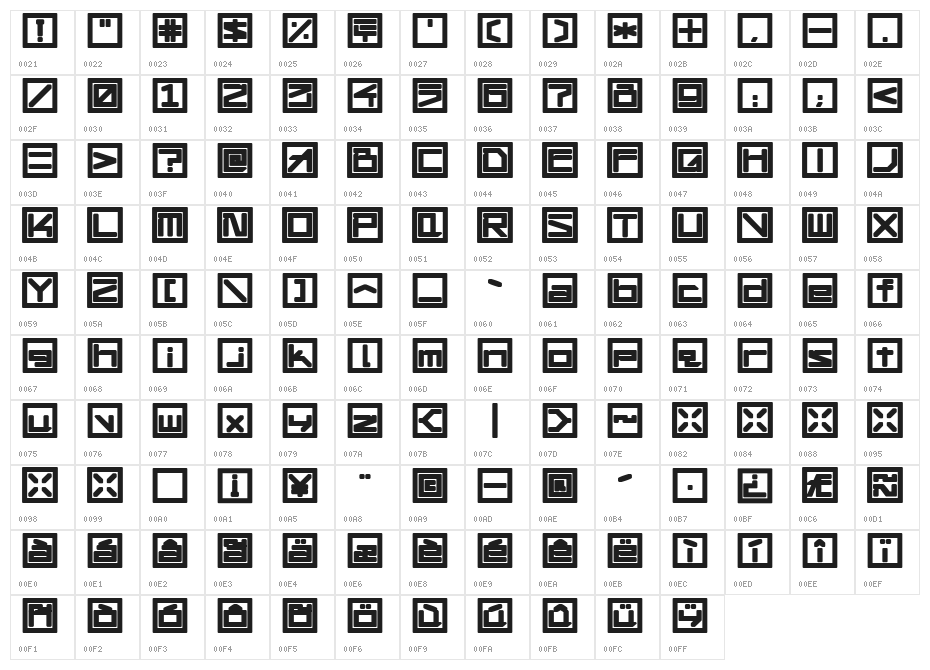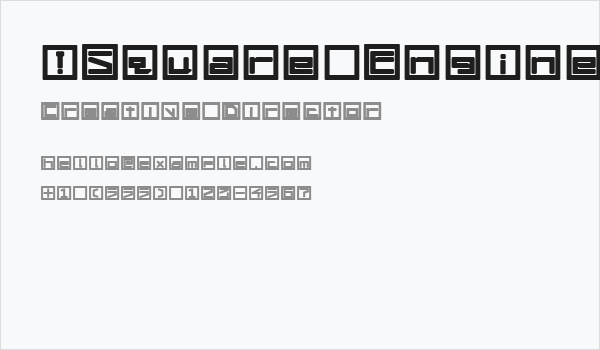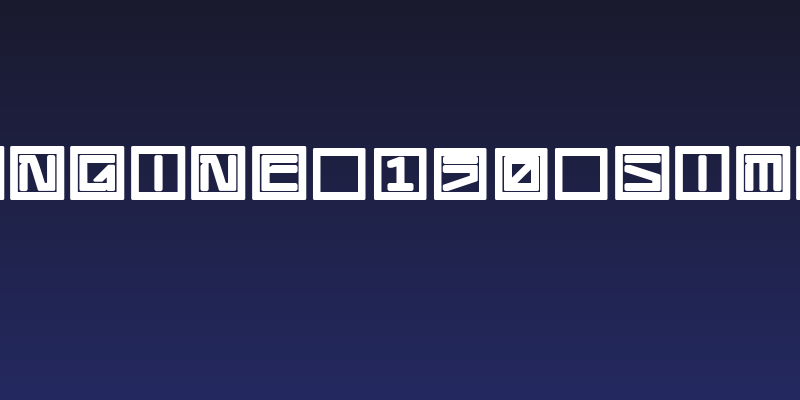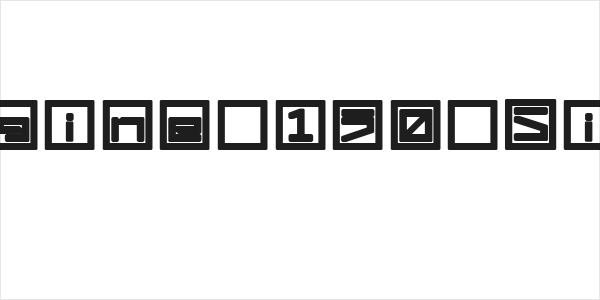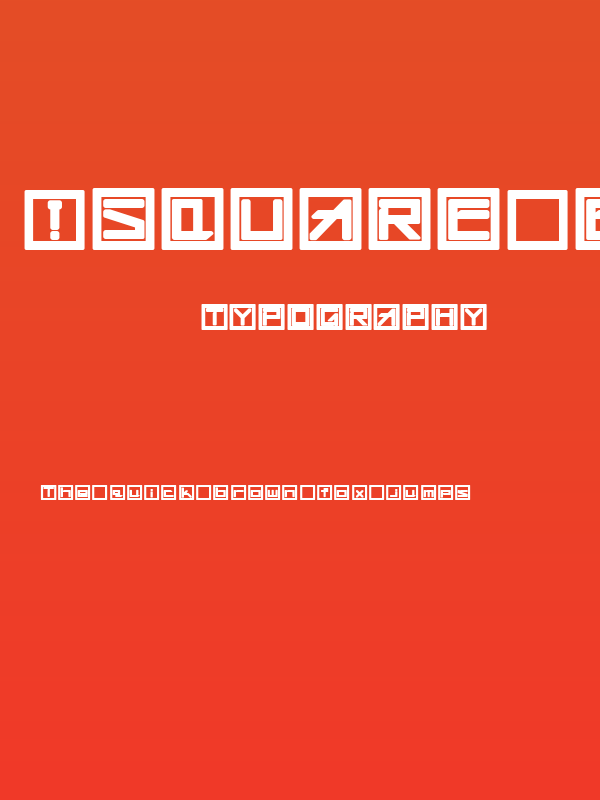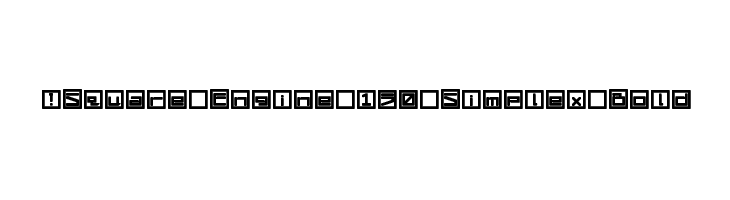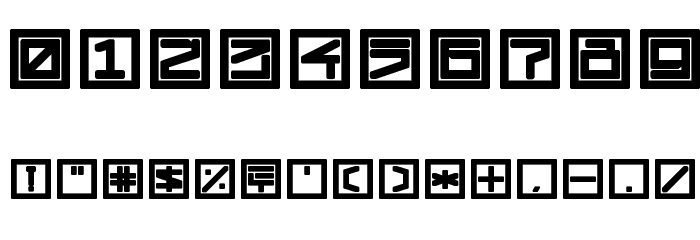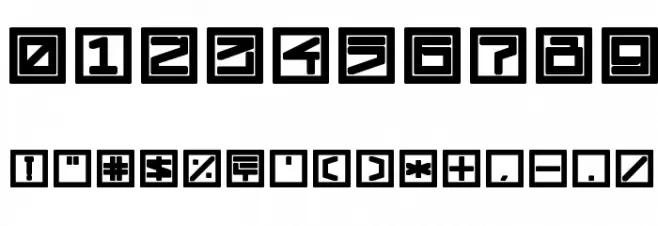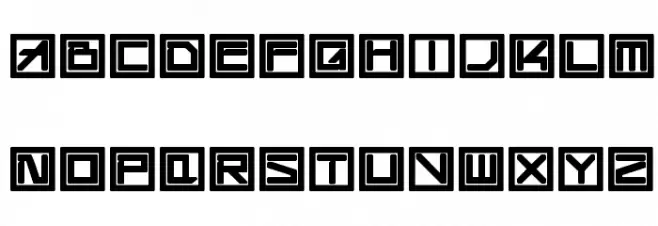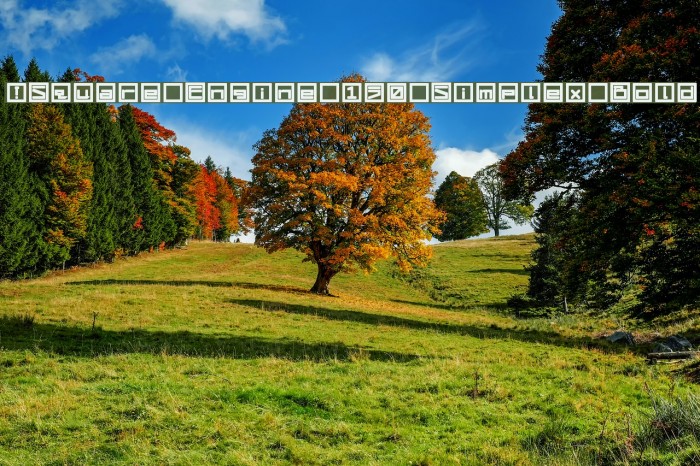
!Square Engine 150 Simplex Bold Font
| Anwendungsfall | Logos, Headlines, Posters |
| Vorgeschlagene Projekte | Ideal for technology-themed designs, video game graphics, posters, and branding that requires a futuristic and bold statement. |